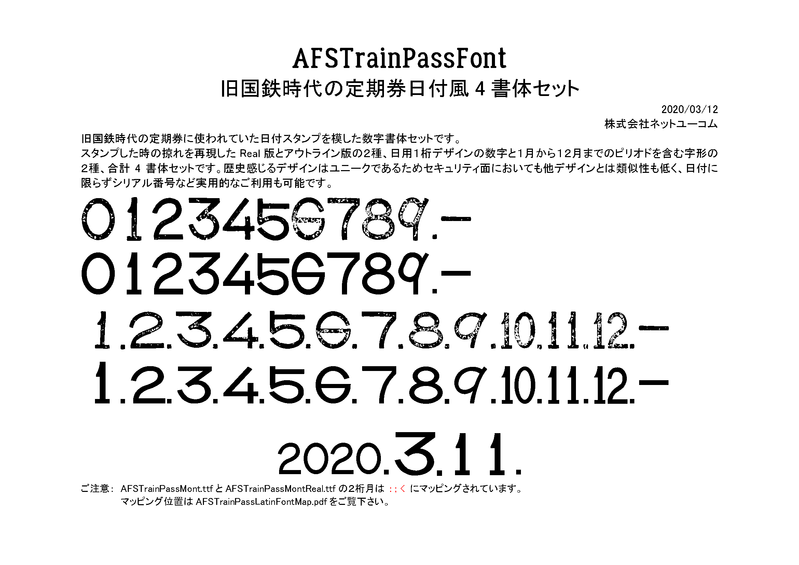
【文字種】
数字書体
【収録書体】
スタンプした時の掠れを再現したReal 版とアウトライン版の2種、日用1桁デザインの数字と1月から12月までのピリオドを含む字形の2種、合計4書体セットです。
旧国鉄時代の定期券に使われていた日付スタンプを模した数字書体セットです。
歴史感じるデザインはユニークであるためセキュリティ面においても他デザインとは類似性も低く、日付に限らずシリアル番号など実用的なご利用も可能です。